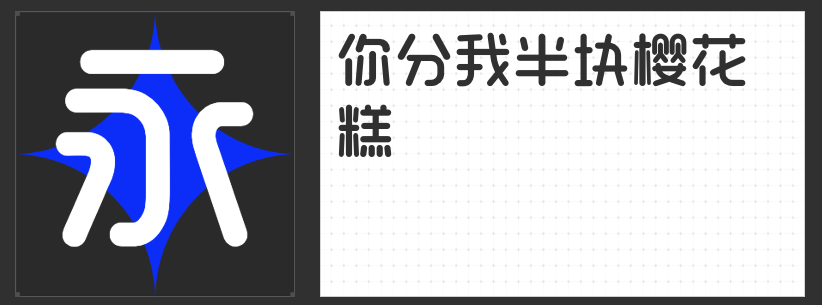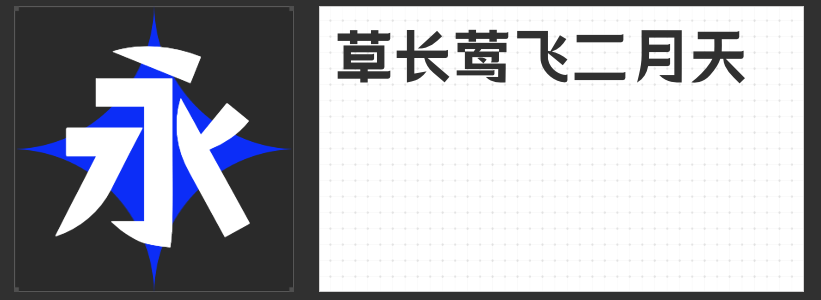
四款风格化字库字体推荐:为饰品包装注入独特美学基因
饰品包装设计是品牌与消费者建立情感联结的第一道视觉触点,而字体的选择往往决定了整体设计的调性与记忆点。以下四款各具美学特质的字库字体,以独特的结构语言与视觉张力,为饰品包装设计提供多元化的创意表达空间。
以几何解构主义重塑汉字形态,棱角分明的直线笔画与镜像对称的撇捺处理,赋予文字强烈的未来科技感。中宫舒展的方正结构,既保持了视觉平衡,又通过去钩化设计消解了传统黑体的机械感。这款字体适合追求极简主义与先锋态度的饰品品牌,其理性克制的美学语言,能精准传递现代珠宝的精致质感与工艺精神。
二、字恋狂澄空 絮风
将手写温度注入数字字体,松紧有致的结构布局与动态字间距,营造出自由灵动的呼吸感。流畅饱满的弧线与平直切角形成微妙对抗,断笔处理带来的留白空间,恰似饰品设计中的镂空工艺,赋予文字轻盈通透的视觉韵律。这款字体尤其适合强调艺术表达与个性主张的轻奢饰品,其变化万千的字形结构,能完美诠释品牌“不拘一格”的创作哲学。
三、创客贴幼稚园体
以圆润无棱角的笔画构建童真语境,所有转折处的软化处理与饱满的负形空间,形成天然的亲和力磁场。这款字体如同饰品包装上的糖果涂层,能瞬间软化消费者的心理防线,特别适合儿童珠宝或少女系配饰品牌,其天真烂漫的视觉特质,能有效强化“可爱经济”的情感共鸣。
四、创客贴春晓宋
在传统宋体基础上进行锋芒化改造,刀刃般的笔画收尾与横画上挑的装饰性细节,既保留了古典书法的文人气质,又注入现代设计的锐度表达。这种刚柔并济的美学平衡,使其成为新中式饰品包装的理想选择,能精准传递东方美学的当代转译与创新精神。
从理性几何到感性手写,从童真趣味到锋芒毕露,这四款字体以截然不同的设计路径,共同构建起饰品包装设计的多维美学体系。设计师可根据品牌基因与产品定位,选择最具共鸣的字体语言,让文字成为诠释品牌价值的第一件“视觉饰品”。